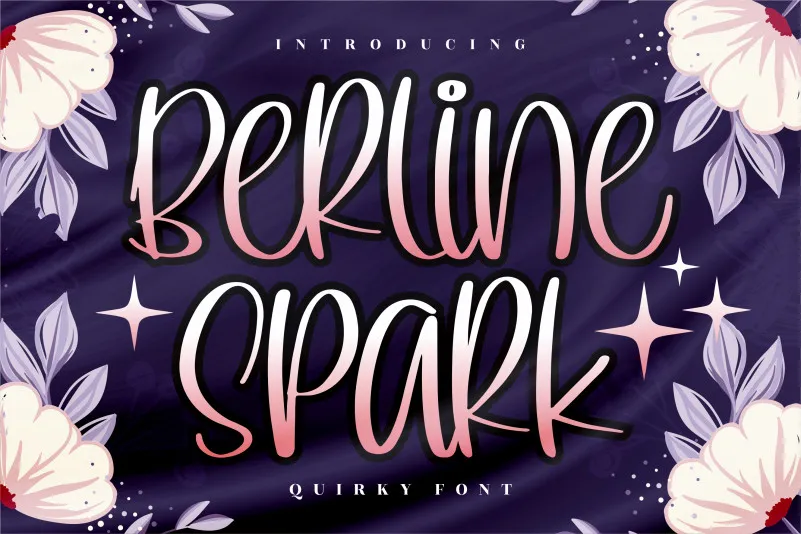
Esta fonte ‘Berline Spark’, criada pelo designer perspectype, é uma opção perfeita para aqueles buscando um touch único e divertido em seus projetos digitais ou impressos. Seu estilo handwritten de escrita descompromissado se destaca, tornando-a uma escolha ideal para uma ampla gama de aplicabilidades, desde logomarcas e identidades de marca até design de móveis, embalagens de produtos, adesivos, camisetas ou até mesmo para capas de livros. Além disso, ela também é perfeita para criações como cartões de visita, convites, cartões de cumprimento, etiquetas, fotografias e até mesmo para criar efeitos únicos em eventos especiais. Com um toque de estranheza e uma pitada de encanto, a ‘Berline Spark Font’ traz o brilho desejado para qualquer projeto que busque aquela atmosfera peculiar, sem abrir mão do encanto e personalidade única.